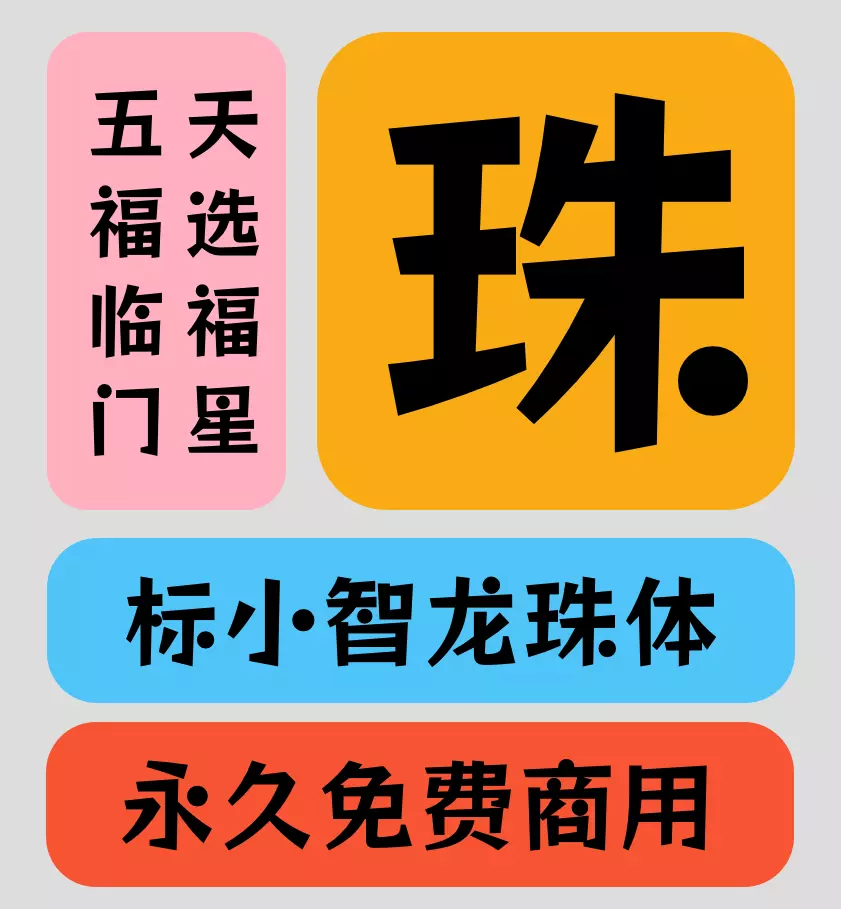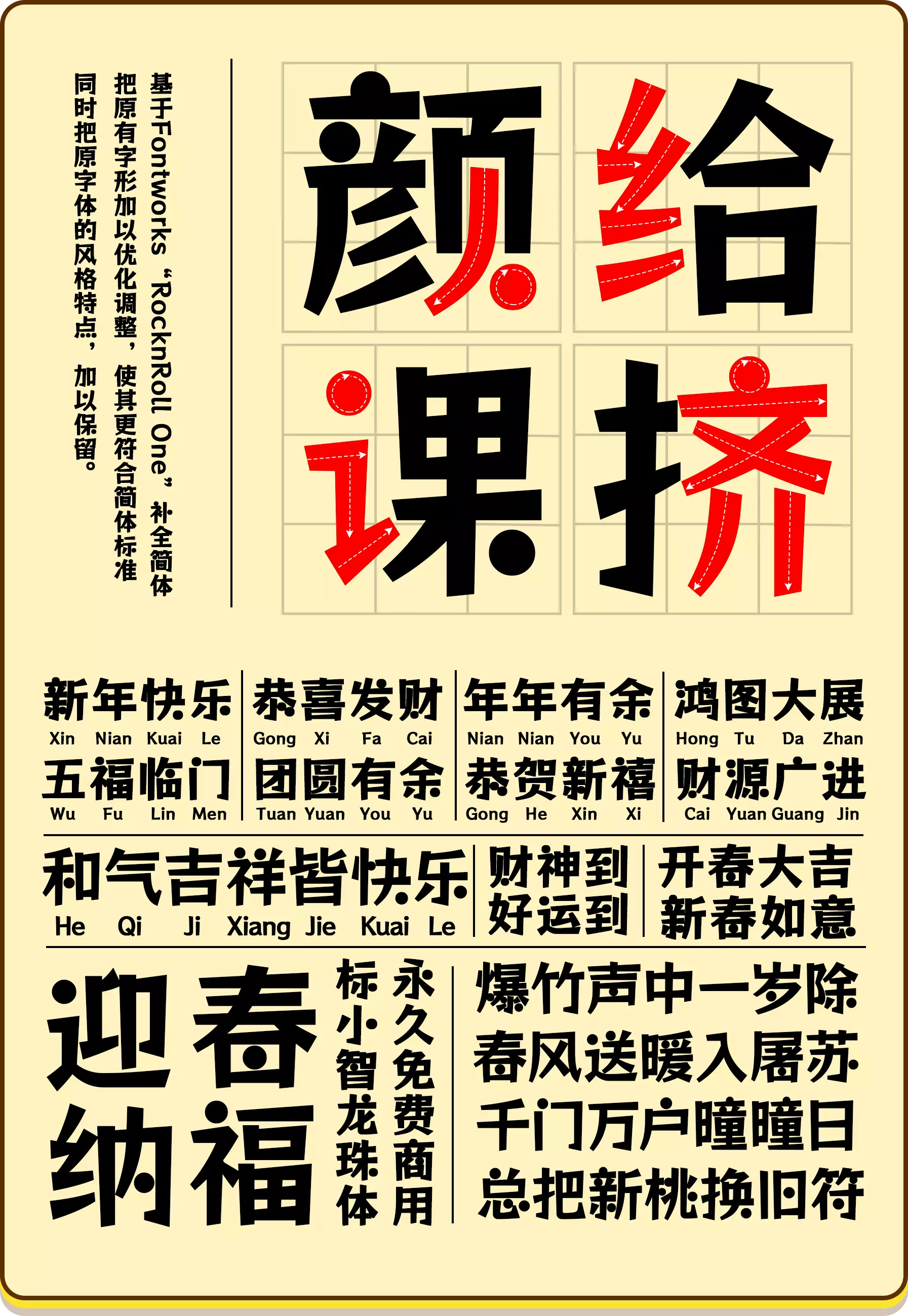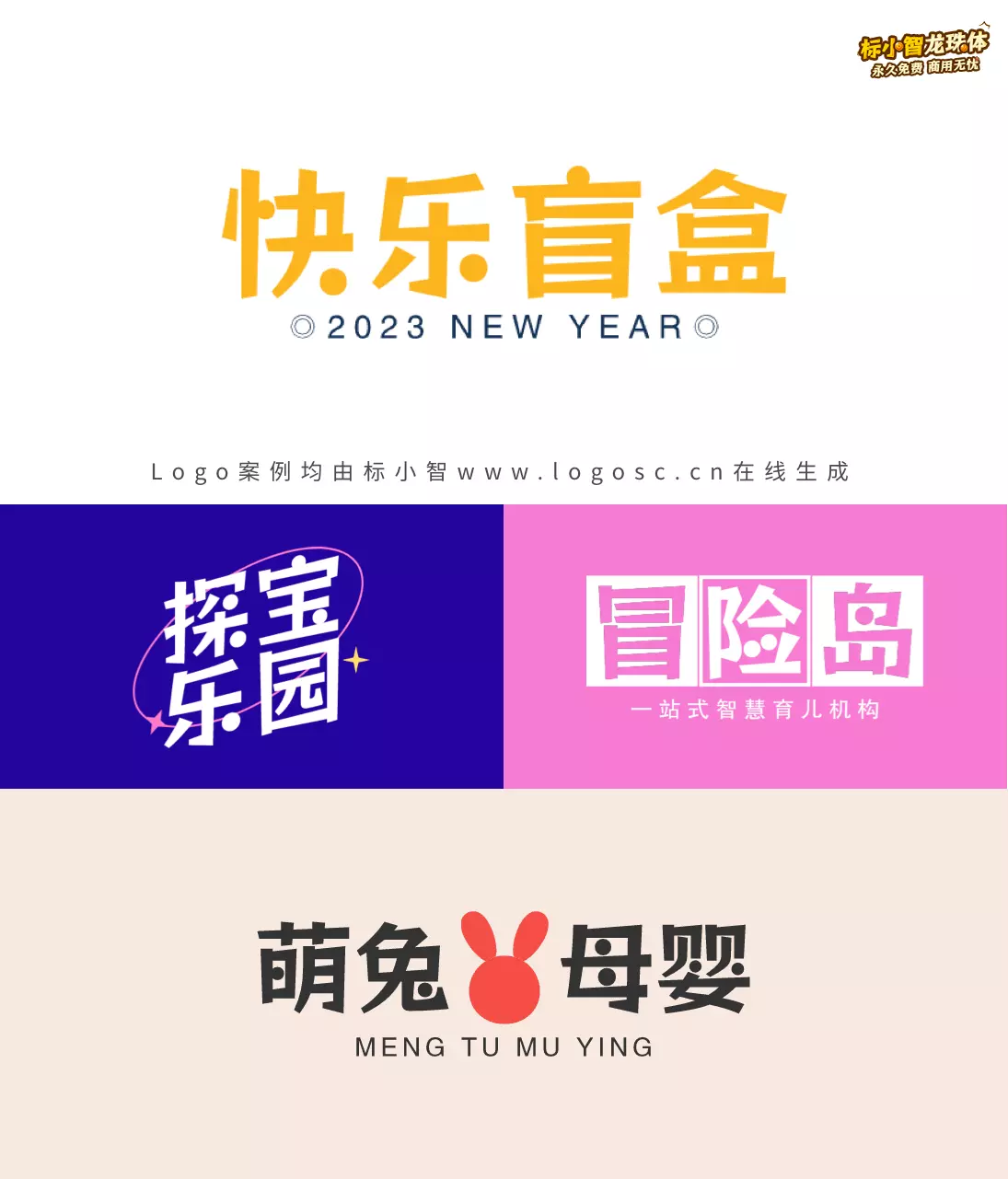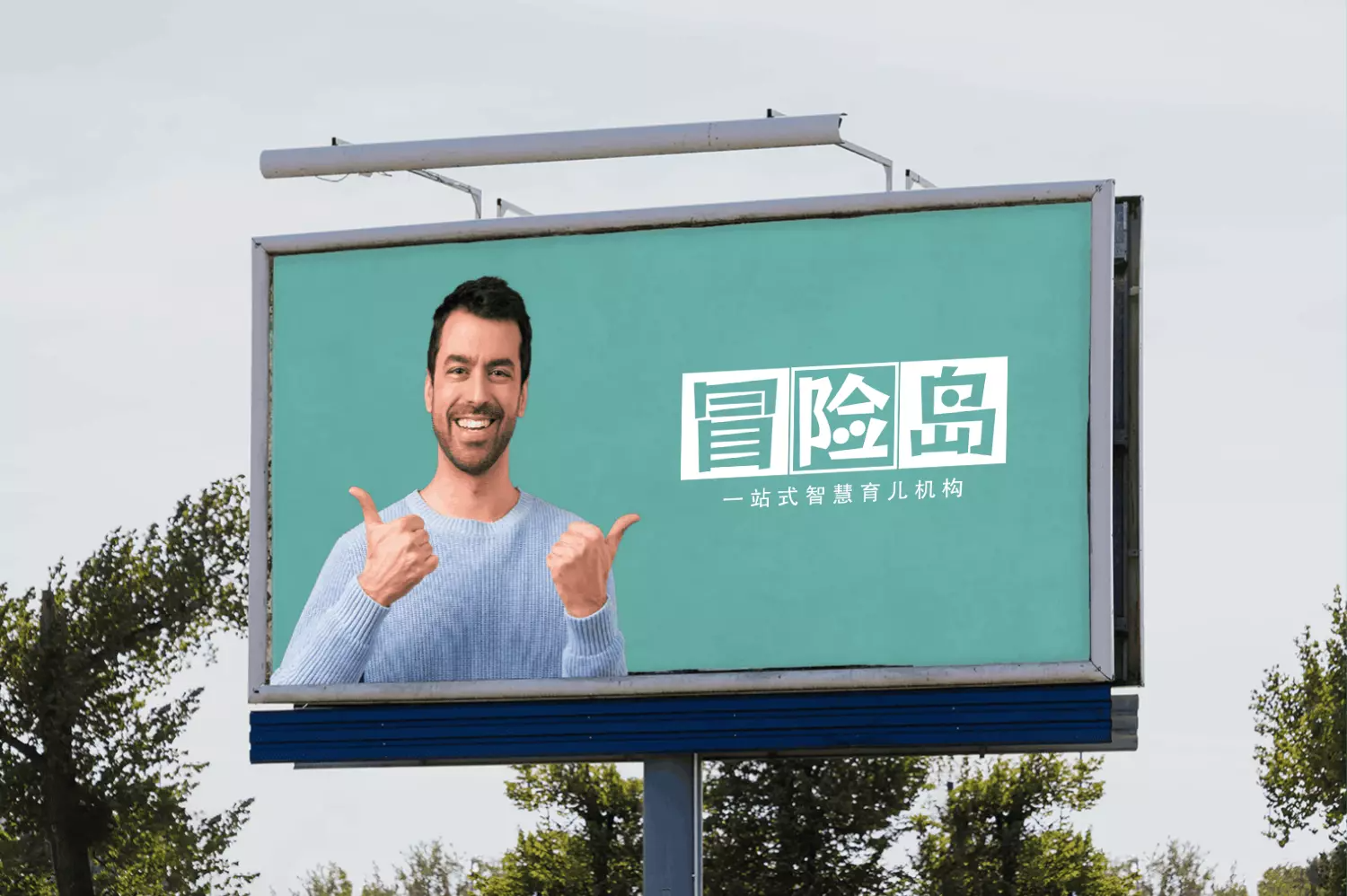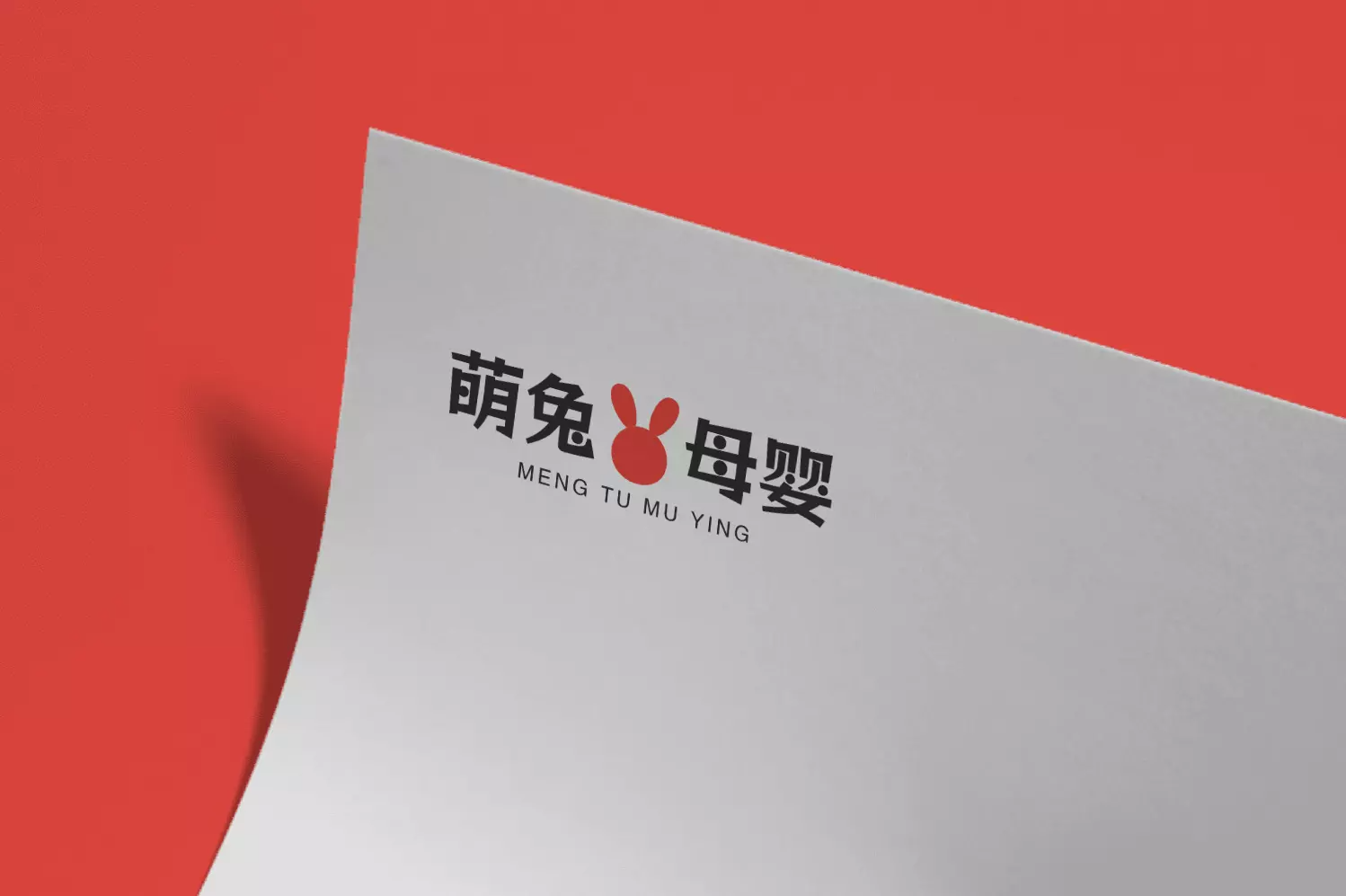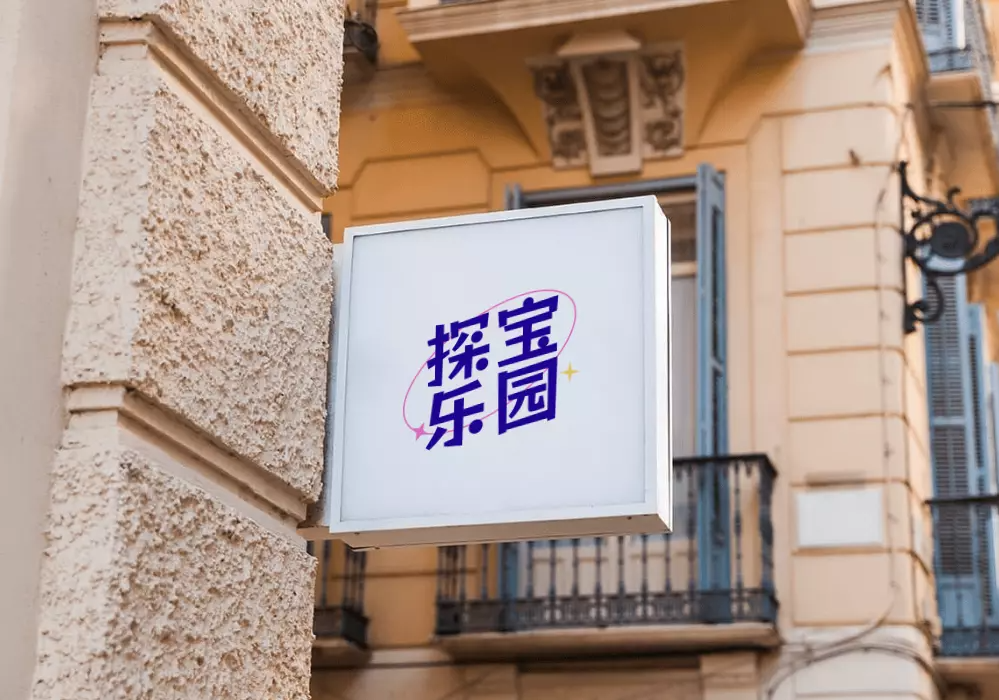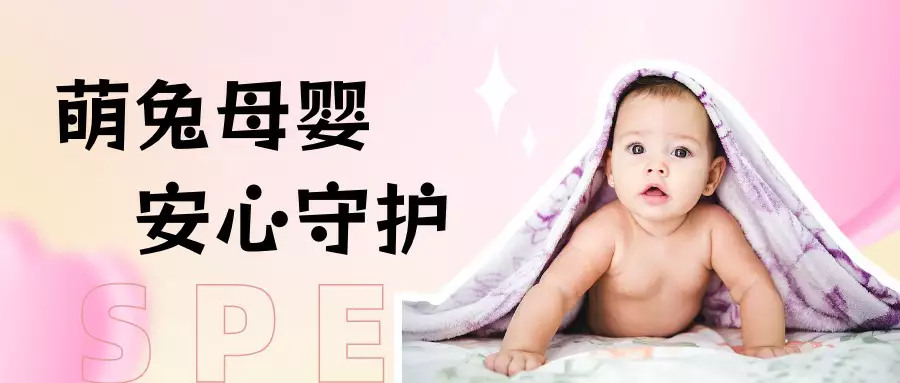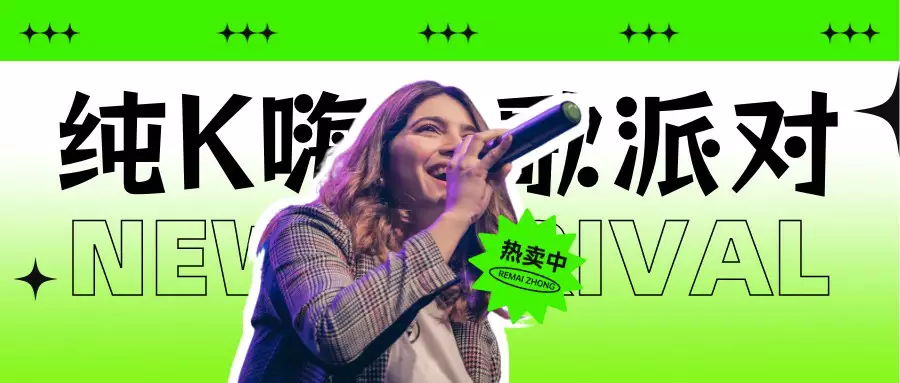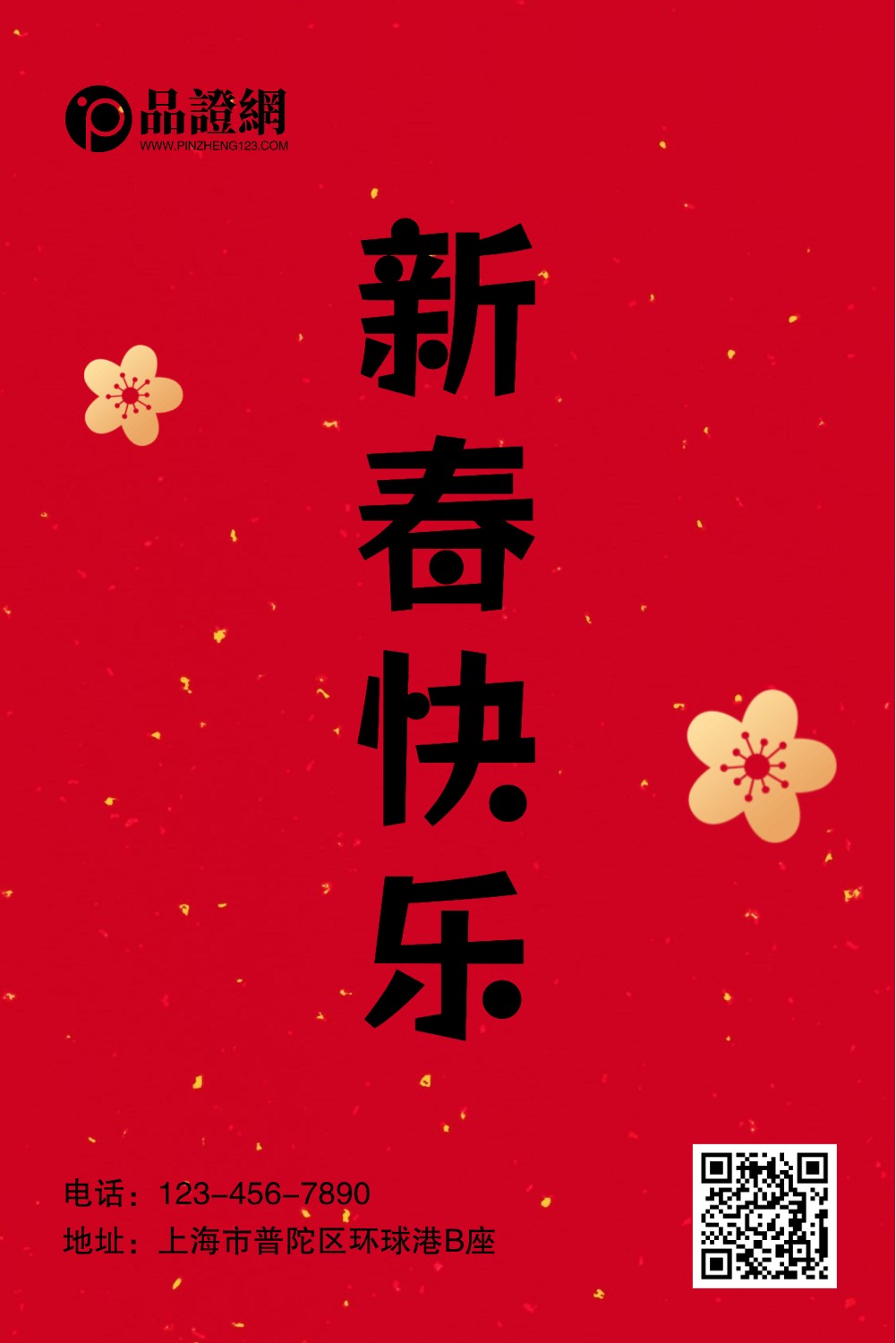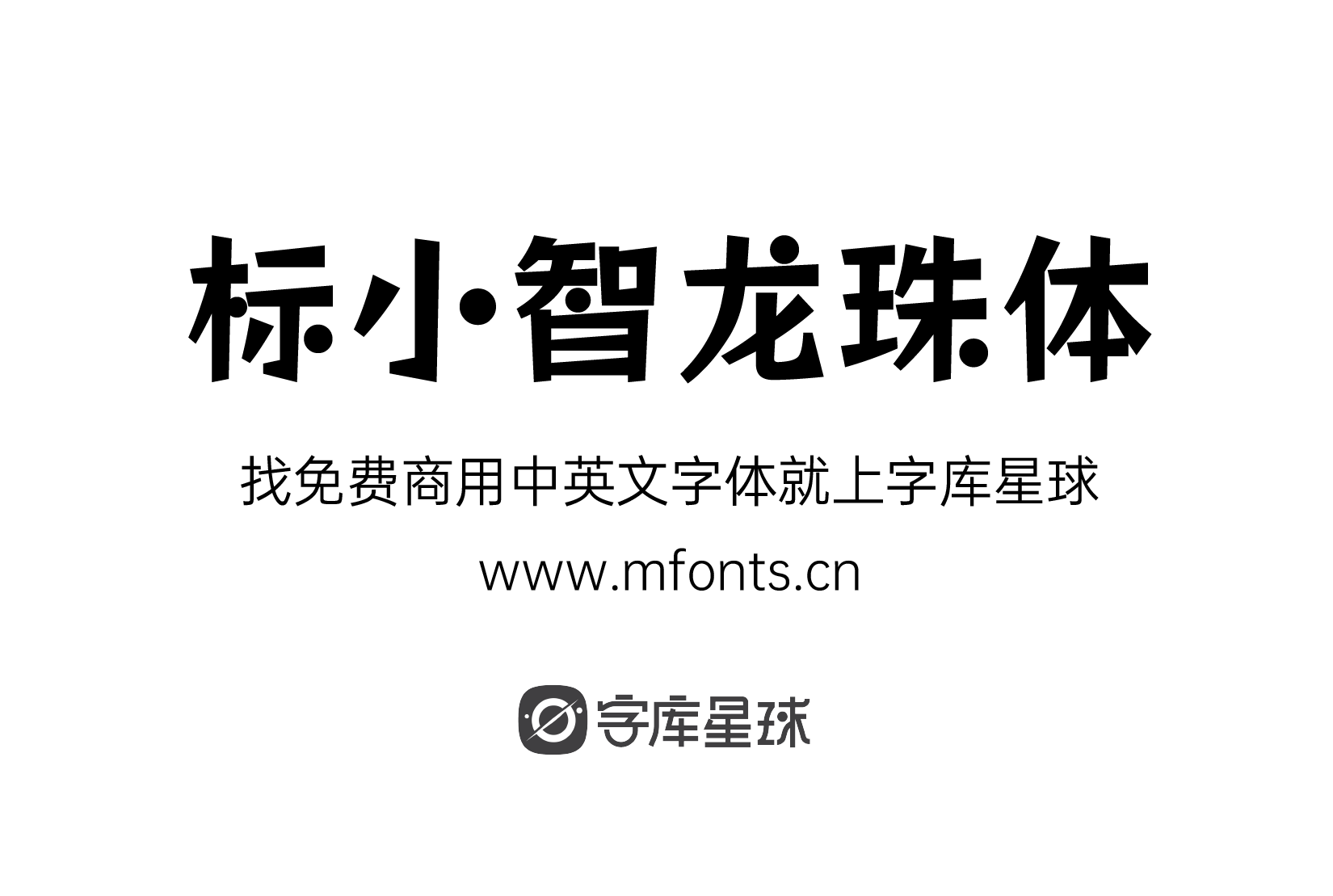
标小智龙珠体是基于日本著名字体设计公司Fontworks免费开源的摇滚乐 One(日文名:ロックンロール)字体进行简体字补充的一款字体。
标小智龙珠体采用了原始的流行风格字体,力度不同的笔触增加了动量,龙珠体整体上比较硬朗,字体笔画粗细变化制作动感,而这款字体最大的特点就是这圆点(龙珠)点缀了,用龙珠代替部分笔画,让字体变得更加生动活泼,气质也更加鲜明有记忆点。
应用展示
文章标题:标小智龙珠体